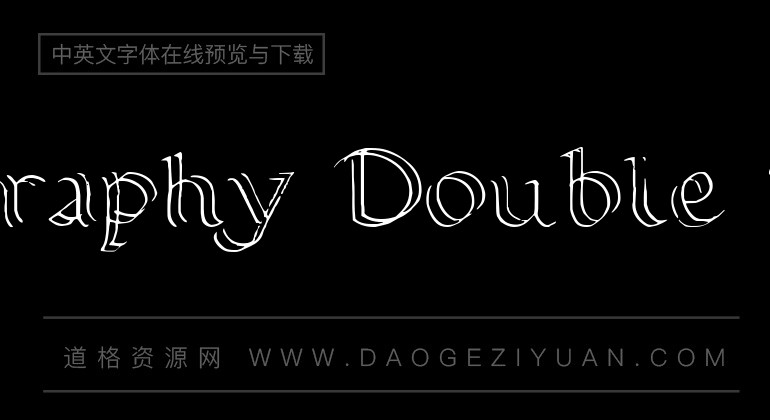
Calligraphy Double Pencil是一款自然风格的手写字体,它有着流畅的笔画和温暖的色调,极具视觉冲击力。这款字体能够给文字带来柔和而优雅的印象,营造出一种温馨而精致的氛围,展现出一种温柔而又活泼的感觉。它可以用于招牌、海报、卡片、T恤等,也可以用于各种宣传材料和广告宣传,特别适合用于婚礼、派对等特殊场合。内容介绍
Calligraphy Double Pencil是一款非常不错的手写艺术字体,具有很好的视觉感,适合于文化类的宣传设计、商业类品牌的广告和产品包装设计以及个性化文字排版等较多场景。